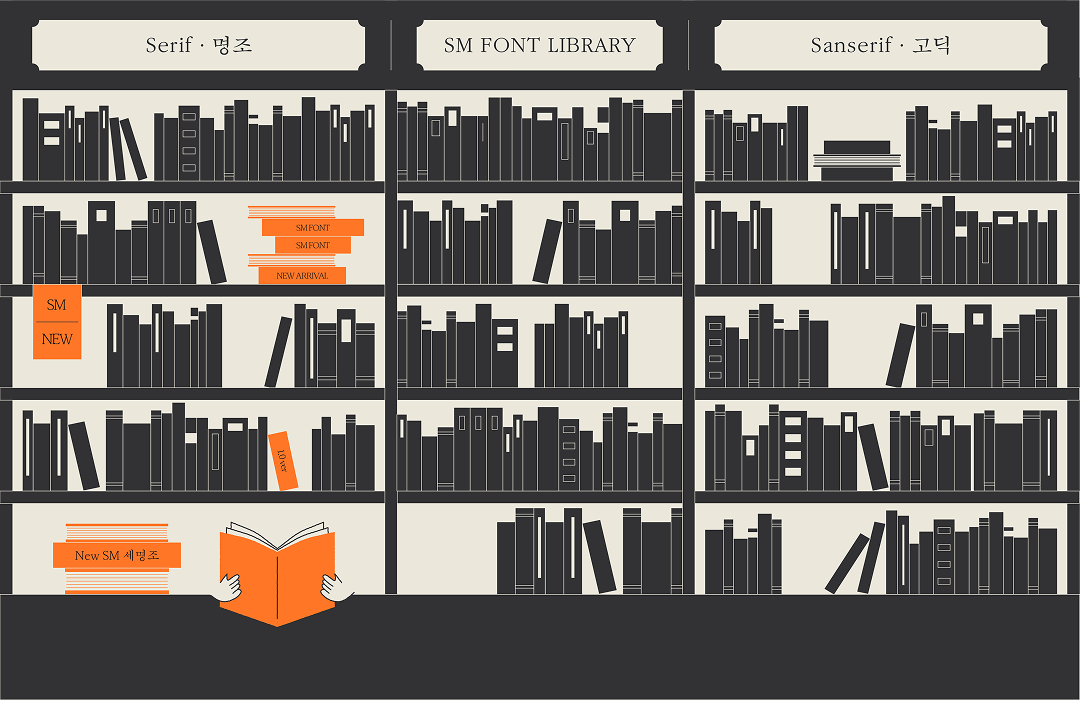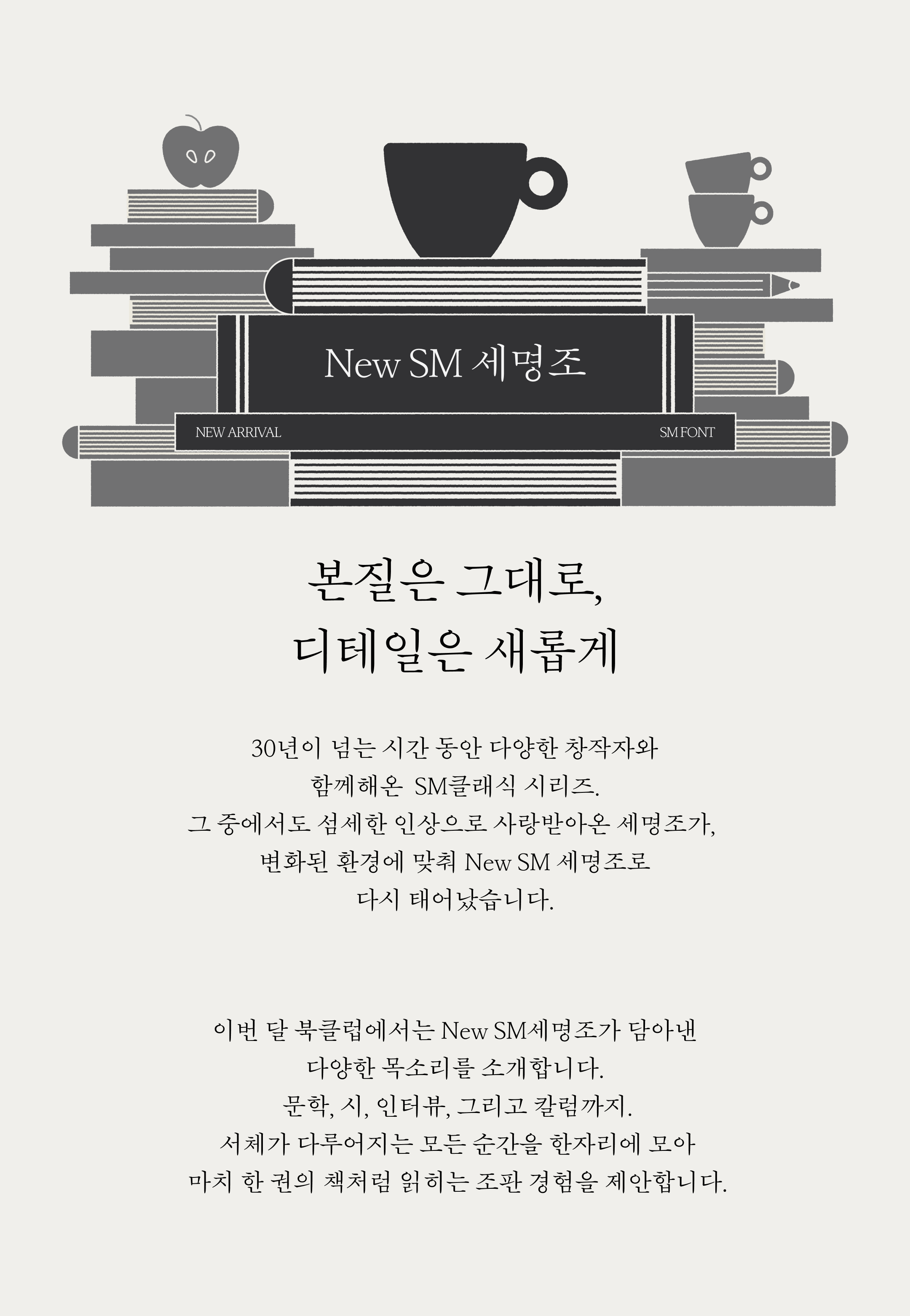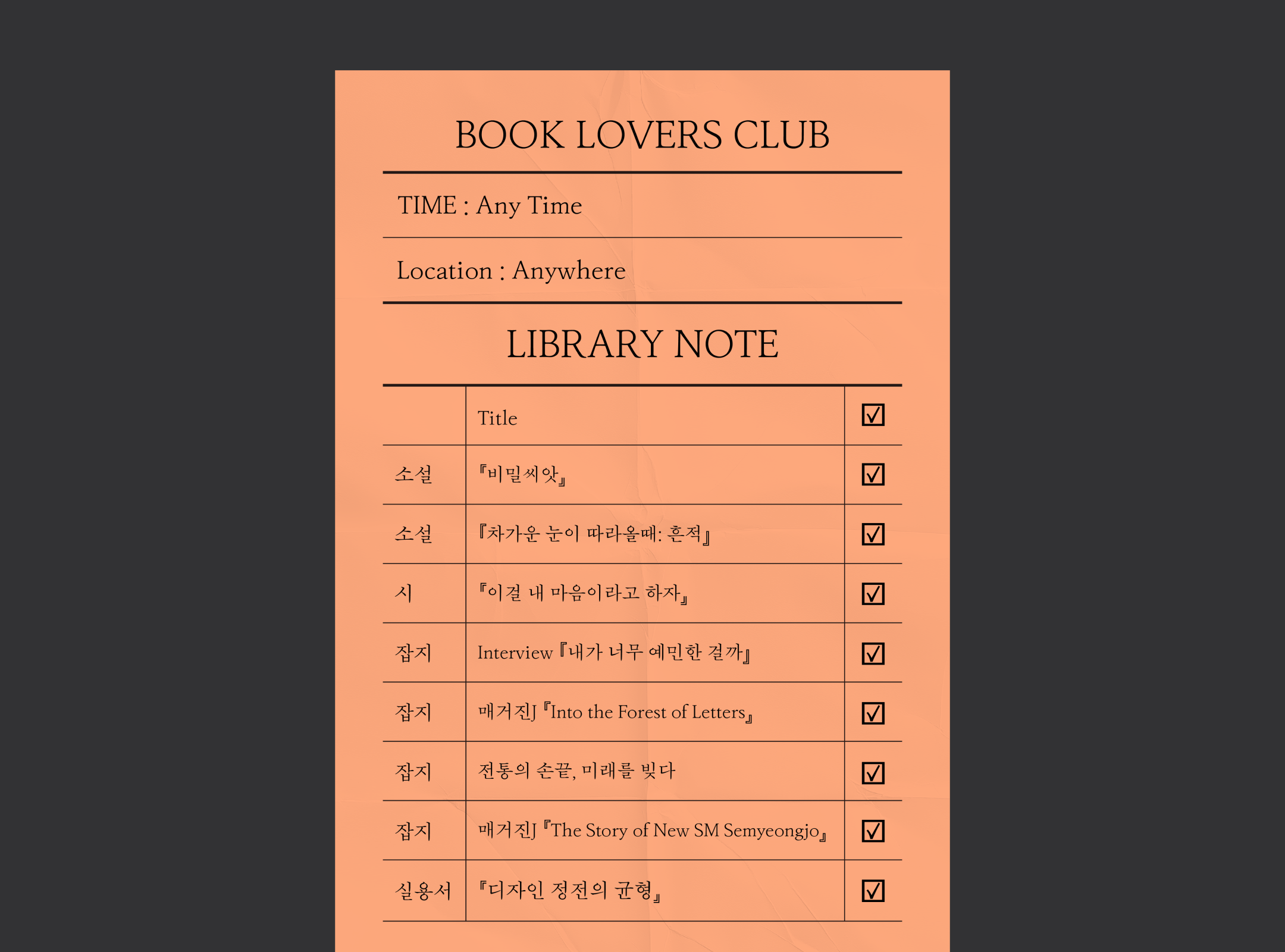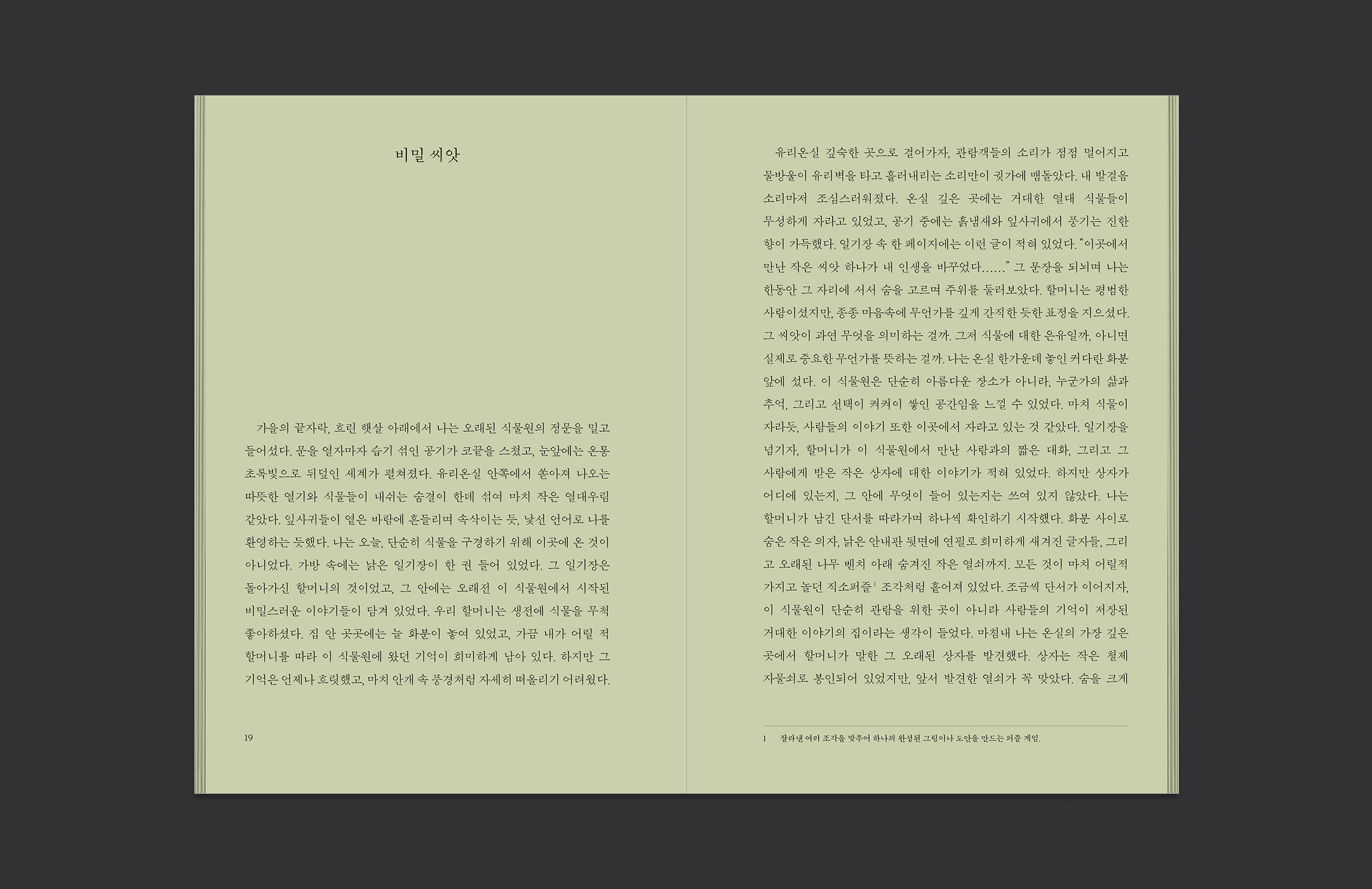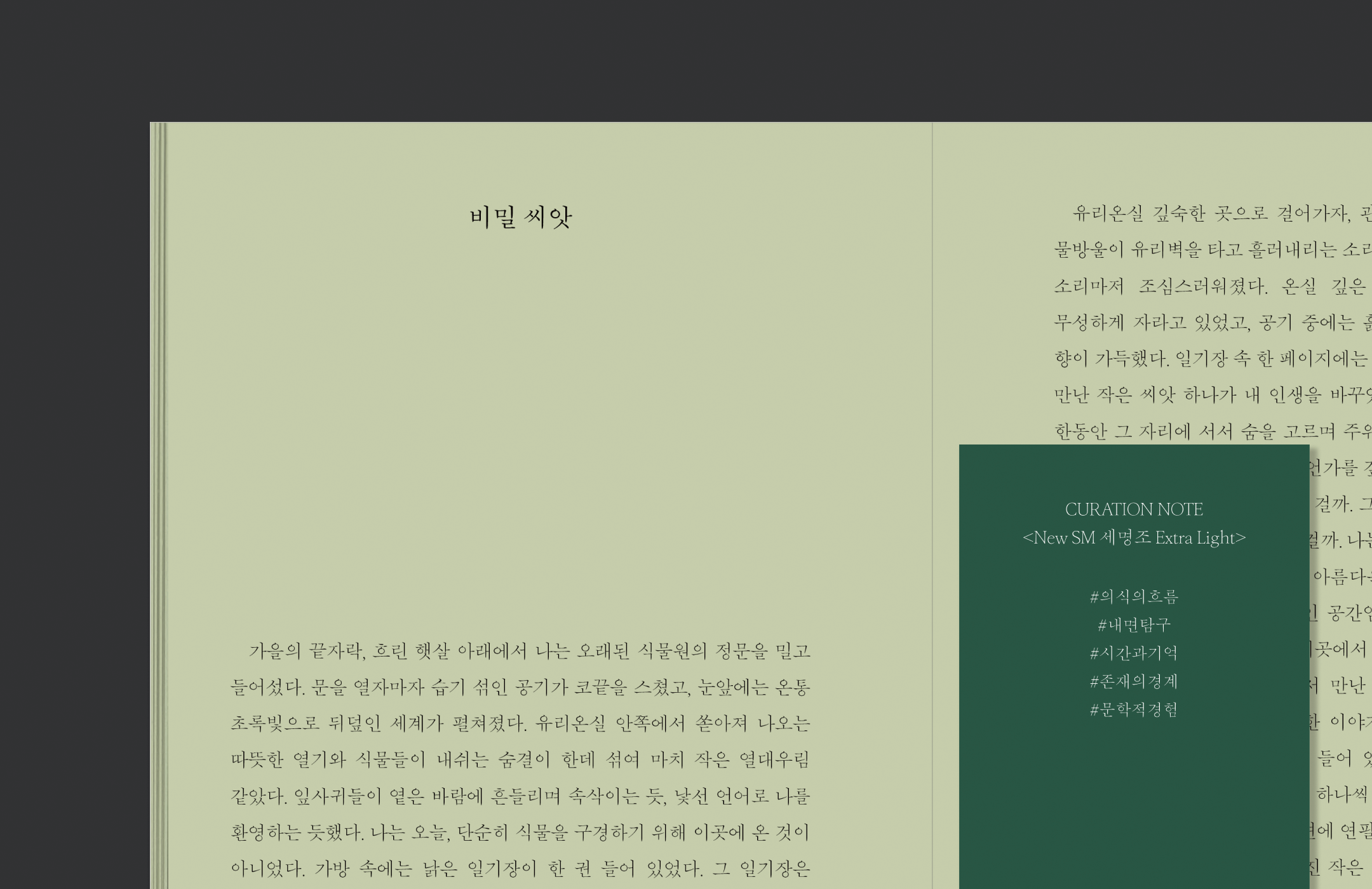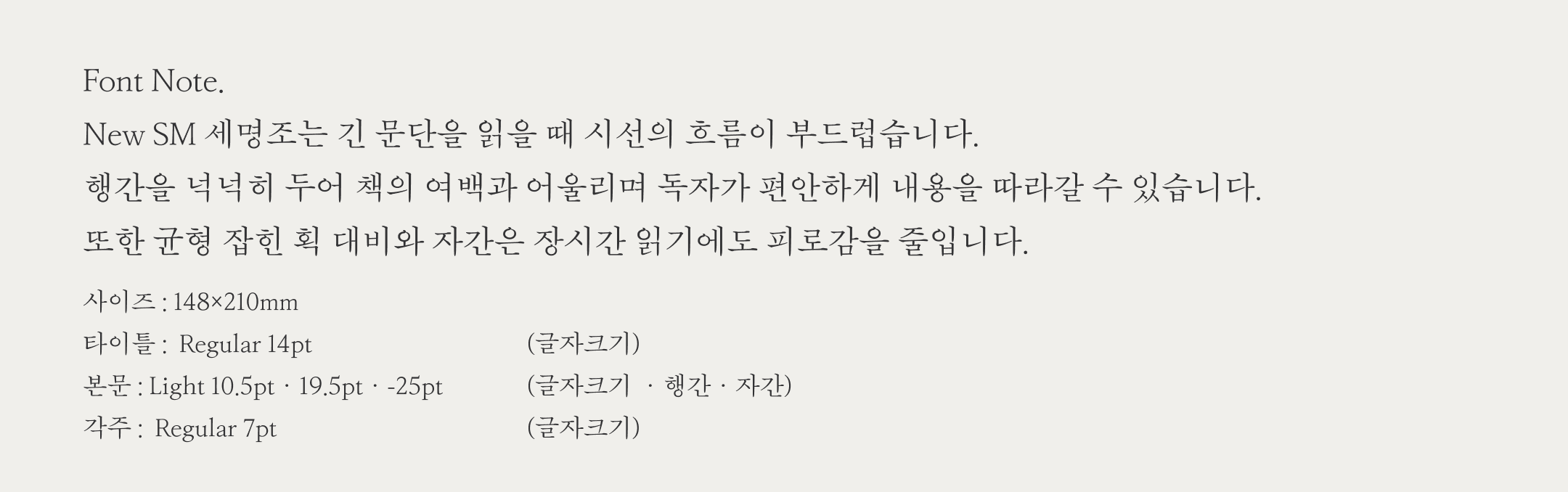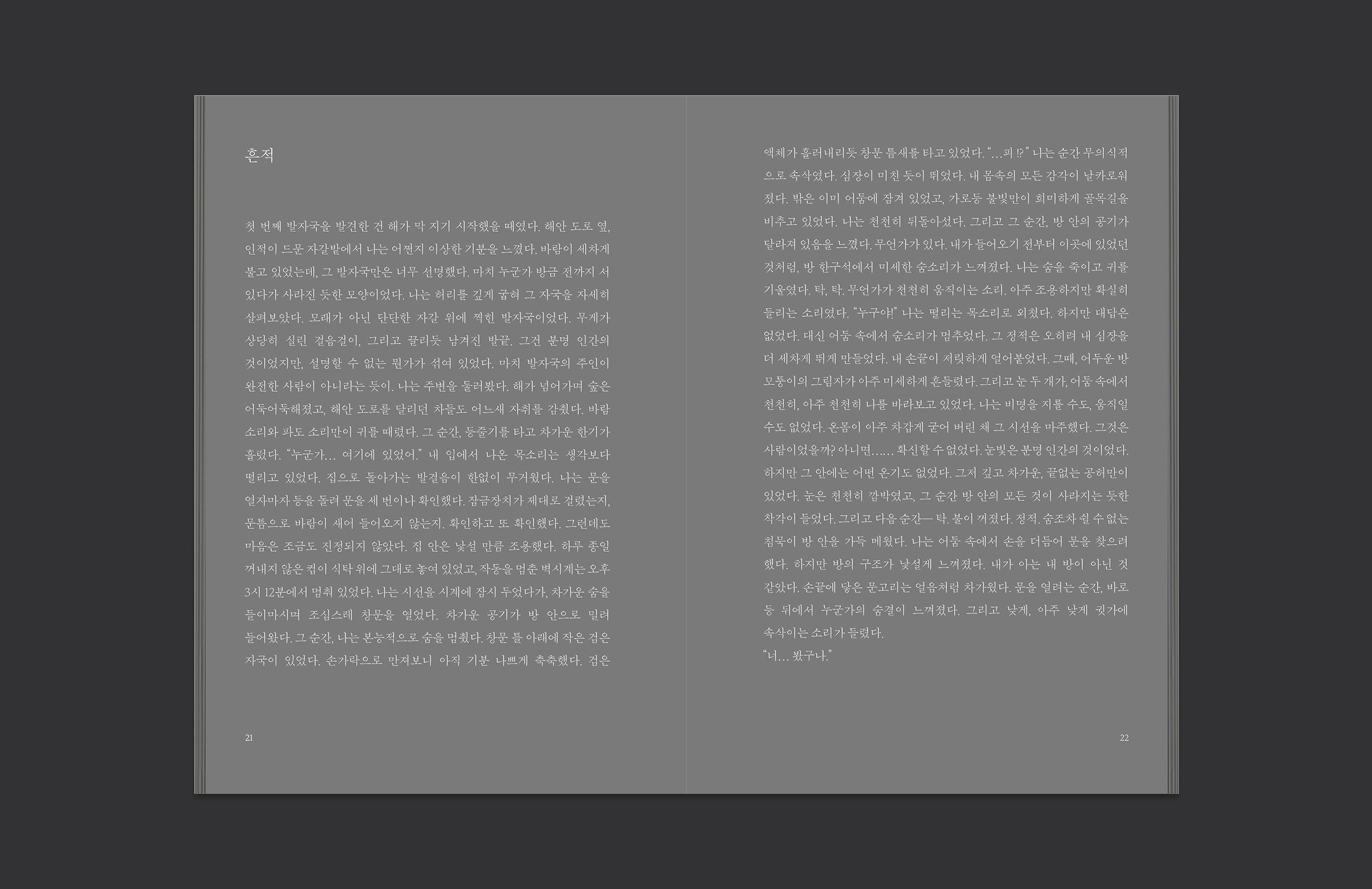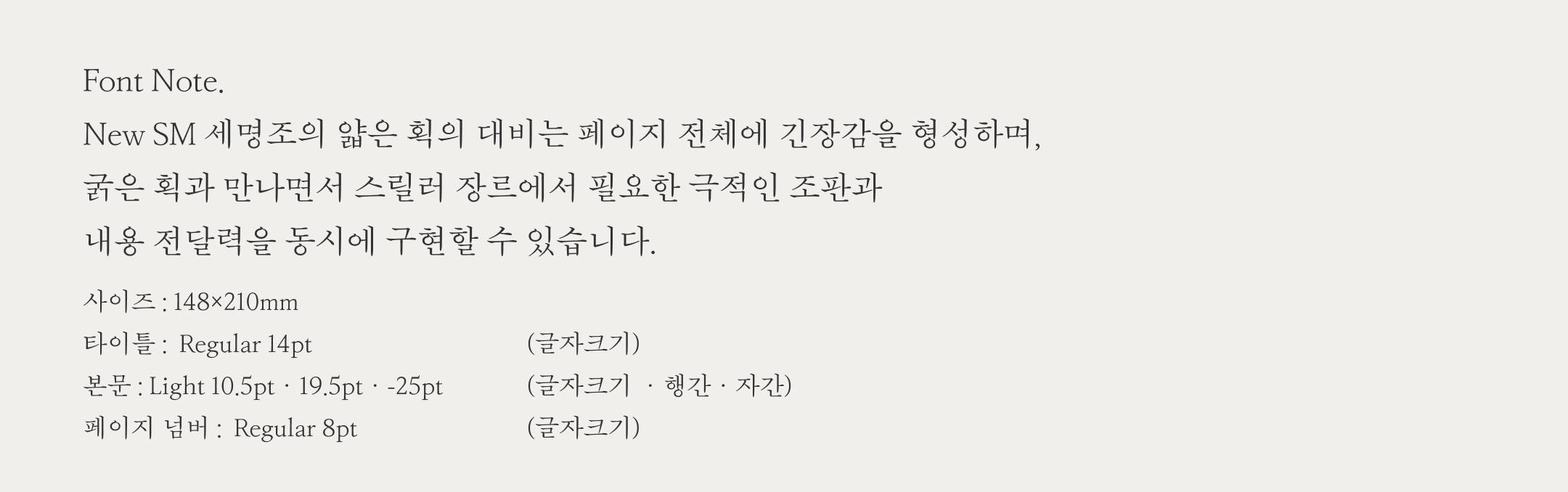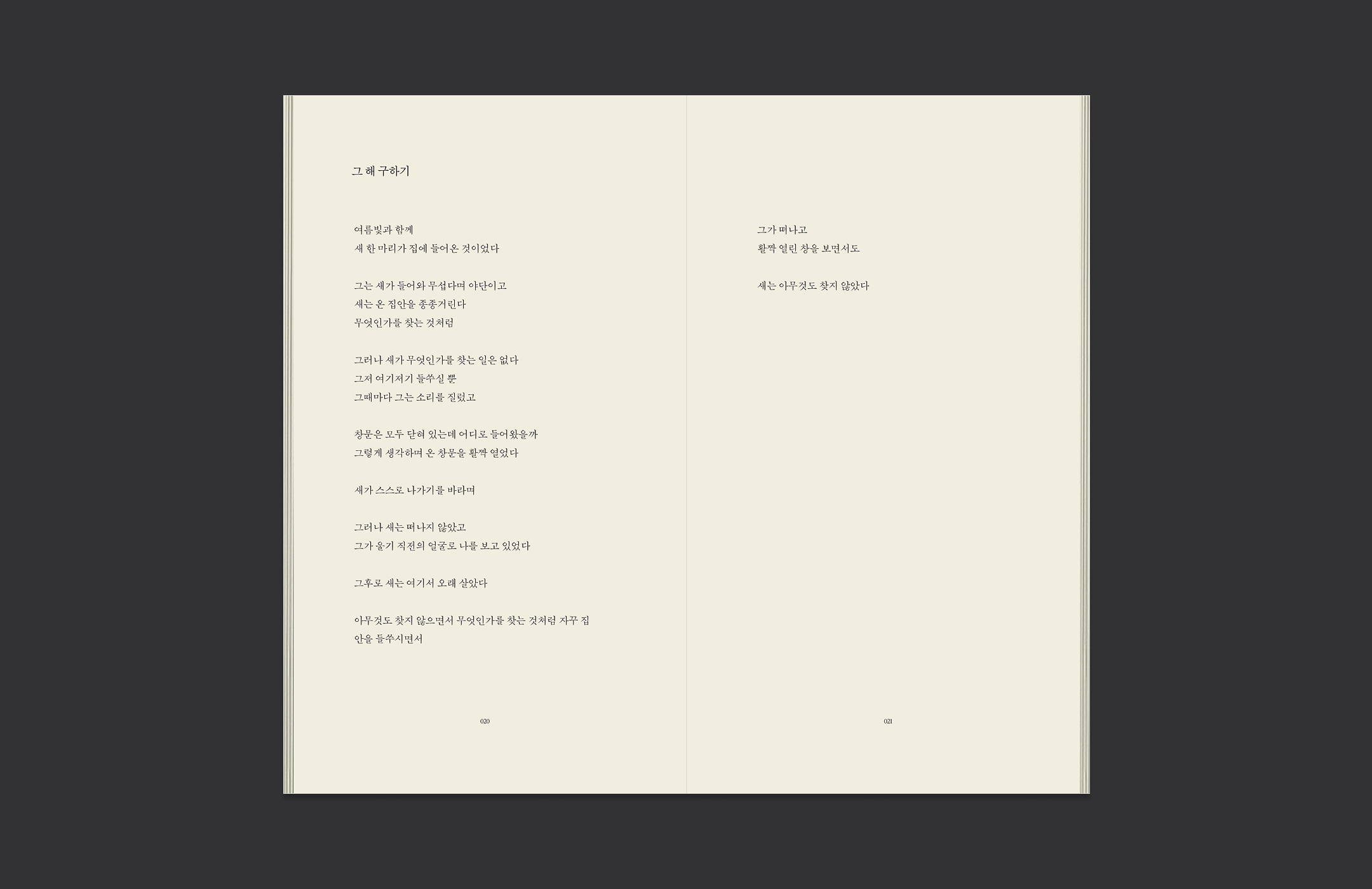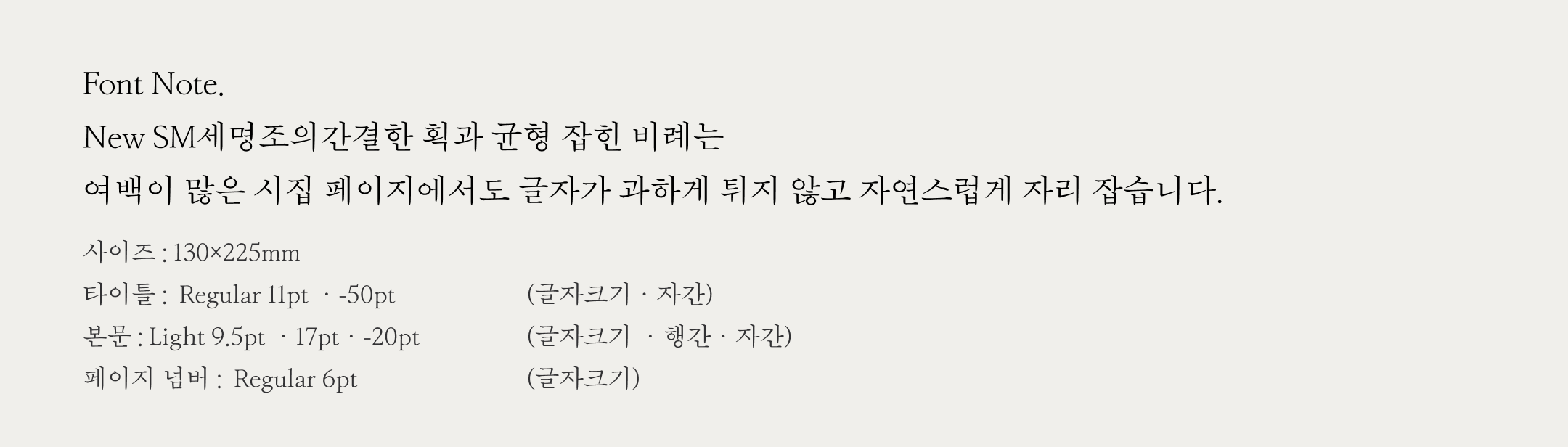
1. ExtraLight
2. Light
3. Regular
지난 1부에서는 세명조 리뉴얼의 핵심 변화와 과정을 함께 살펴보았습니다.
전통을 지키면서도 오늘의 환경에 맞게 다듬어진 서체의 여정을 확인할 수 있었죠.
이번 2부에서는 New SM 세명조가 다양한 매체에서 어떻게 조화를 이루는지를 보여드렸습니다.
지면, 디지털, 그리고 옥외광고까지 확장되는 활용 사례를 통해 서체의 가능성을 확인할 수 있었죠.
세명조가 전통을 지키면서도 오늘의 환경에 맞게 새롭게 태어났음을 느끼셨길 바랍니다.